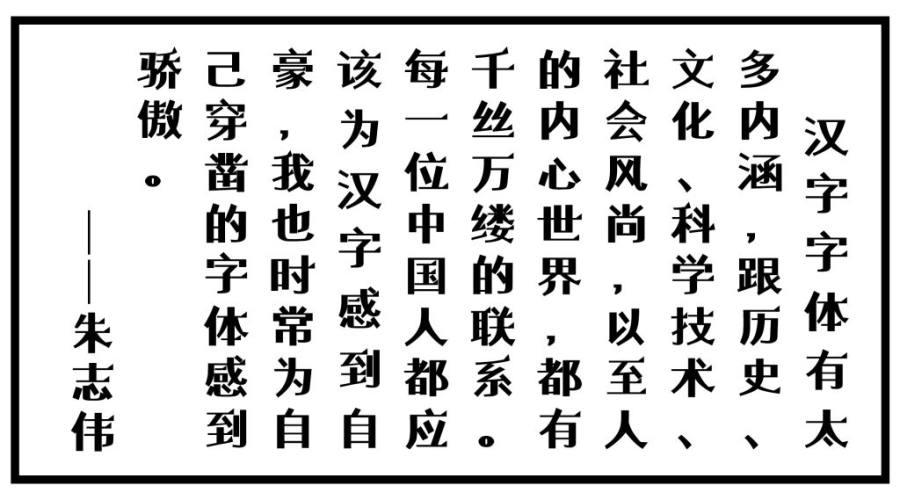
「义启俏黑体」效果展示
黑体对于大家来说都不陌生,
他的正式感让人联想到的总是文章标题,论文标题……乐趣也因此减半,这才有了我们的「义启俏黑体」。
在「义启俏黑体」的设计上,
我们设计师加入了俏皮活泼的视觉效果,可谓是厚重的字形下藏着一颗好动的字心。
还你一个轻松俏皮的黑体!
"每款字都有她存在的理由,
或重或轻,或简或繁,或正或偏,起笔落笔间皆是生活的缩影。"
不同于黑体笔画起落或转折处方方正正或圆润光滑,
没有任何尖角,
义启俏黑体在笔画的横、提、平撇处带有耸肩角,视为笔画起落时欢快的一笔。
「义启俏黑体」打破了黑体横平竖直且粗细一致的风格,
以“横细竖粗”为特点。增强了整体的粗度和黑度,醒目吸睛。
「义启俏黑体」整体风格轻松活泼,以“矢”字为例,
看到这个字的当下,
就想到一个淘气的小孩正蹦跶蹦跶的朝着他心爱的零食跑去,
还不忘甩动他纤细的胳膊。
黑体本身只是装饰性字体,
不是内文字,也不是书法字。但「义启俏黑体」的丰富度,
让他在内文书写中也能有非凡的表现,让黑体摆脱了“标题字体”的标签。
" 在不同的场景里感受他最本真的“形貌”。"
黑体从最初发明时只作为标题使用,到今天已经成为最多变、用途最广泛的基本字体,
无论标题还是内文、注释都试用,
也适用于低像素屏幕上,是互联网时代电子产品上的主要字体。